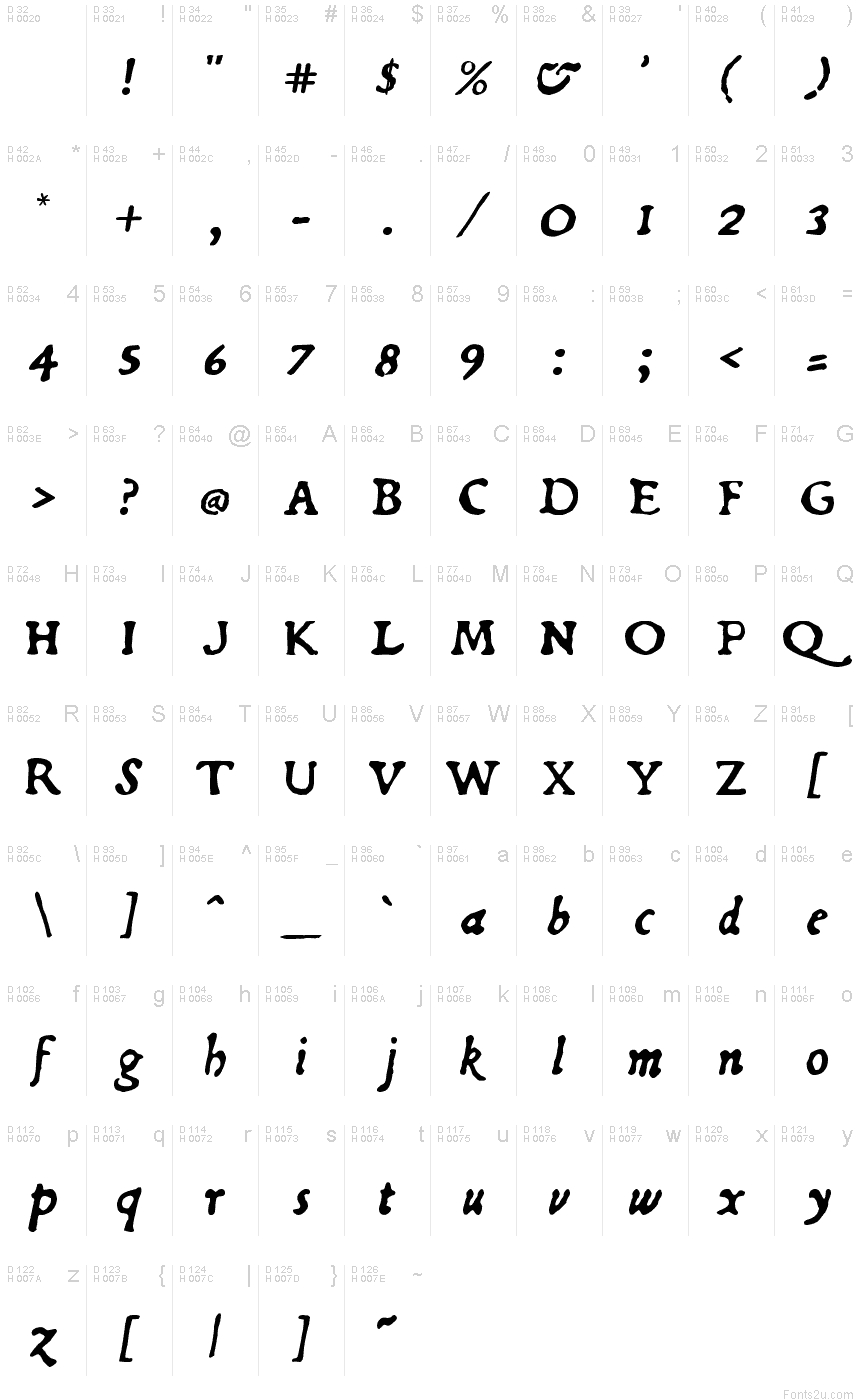
Du Bellay Italic to darmowy, erodowany krój kaligraficzny z rodziny Du Bellay. Jego ciemne, nasycone tuszem pociągnięcia sprawiają wrażenie rysowanych ręcznie i lekko nadgryzionych zębem czasu; poszarpane krawędzie oraz dynamiczne pochylenie nadają słowom niepokornego, starodawnego uroku.
Du Bellay Italic świetnie sprawdza się na okładkach książek, etykietach win, w menu karczm, na mapach fantasy, w zinach poetyckich, na plakatach festiwali folkowych oraz opakowaniach produktów rzemieślniczych, którym odrobina patyny dodaje charakteru. Zastosuj go w dużym rozmiarze i zestaw ten darmowy font z oszczędną szeryfową czcionką lub prostym krojem bezszeryfowym, aby jego surowa faktura i wyrazisty rytm wysunęły się na pierwszy plan.